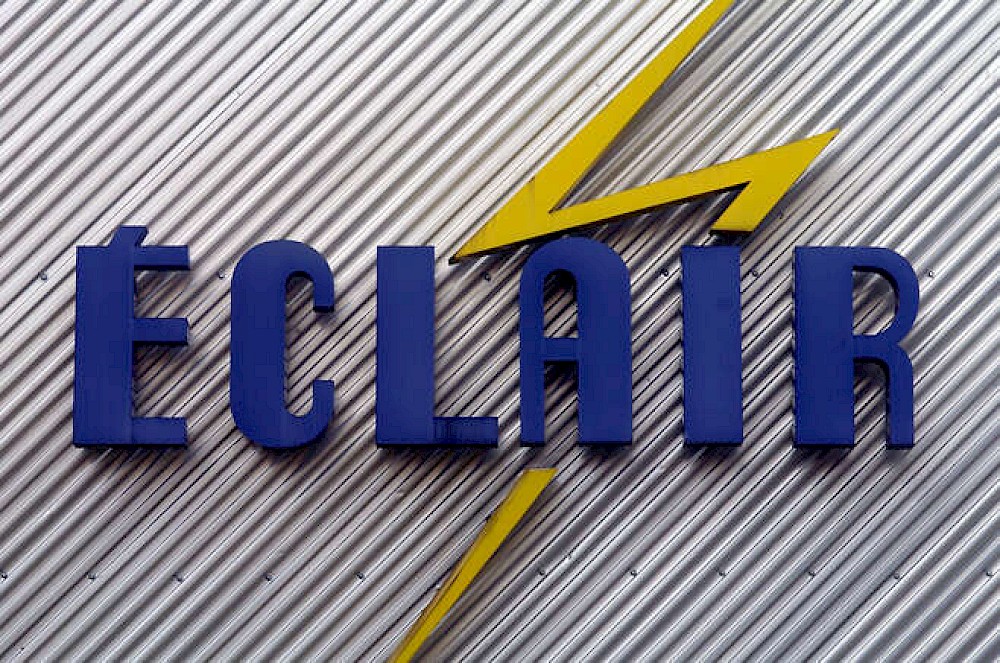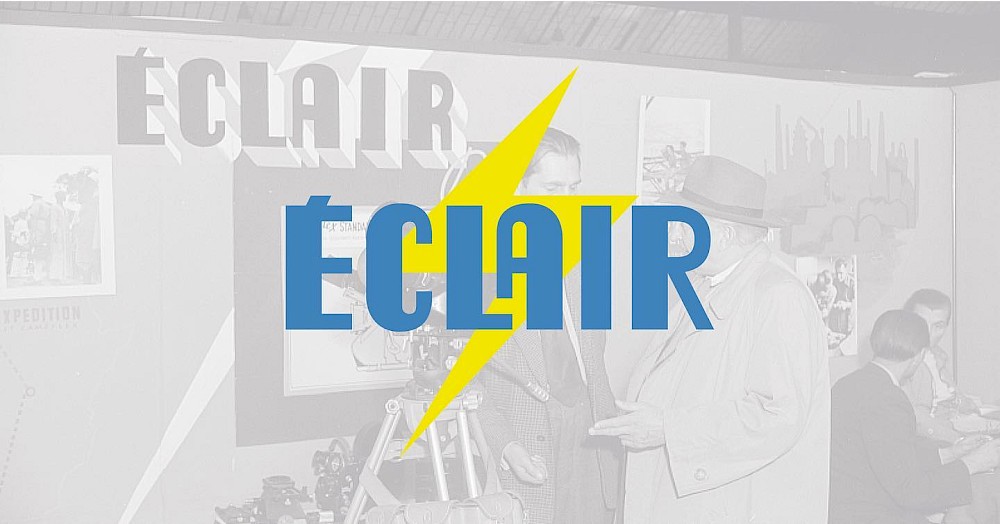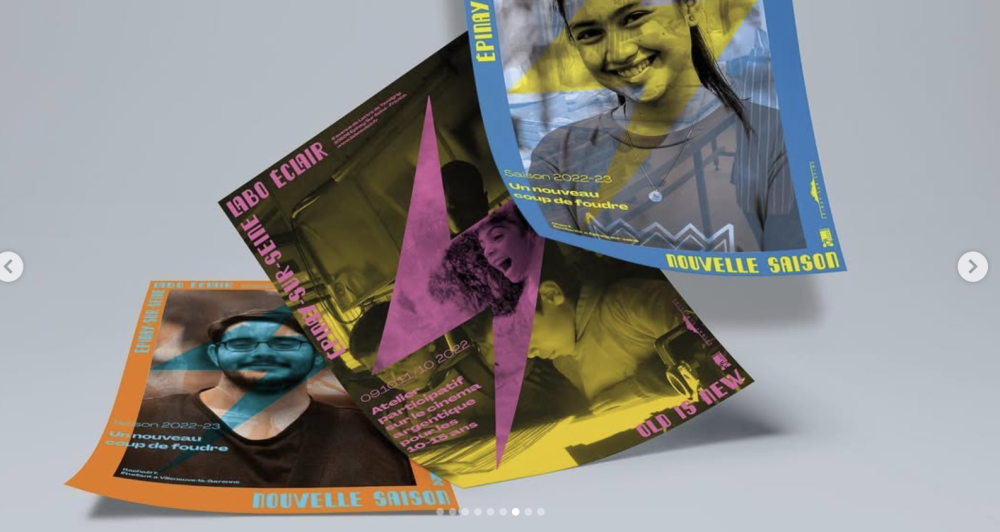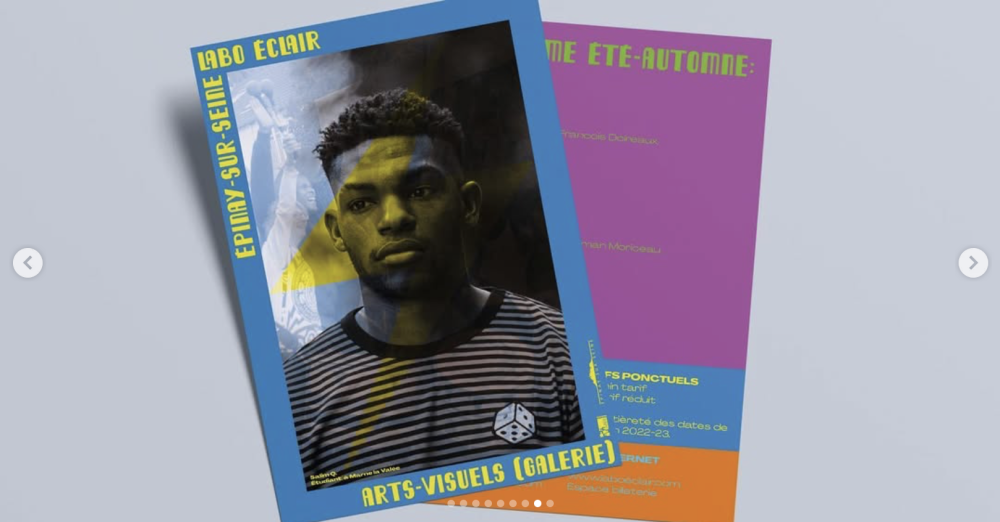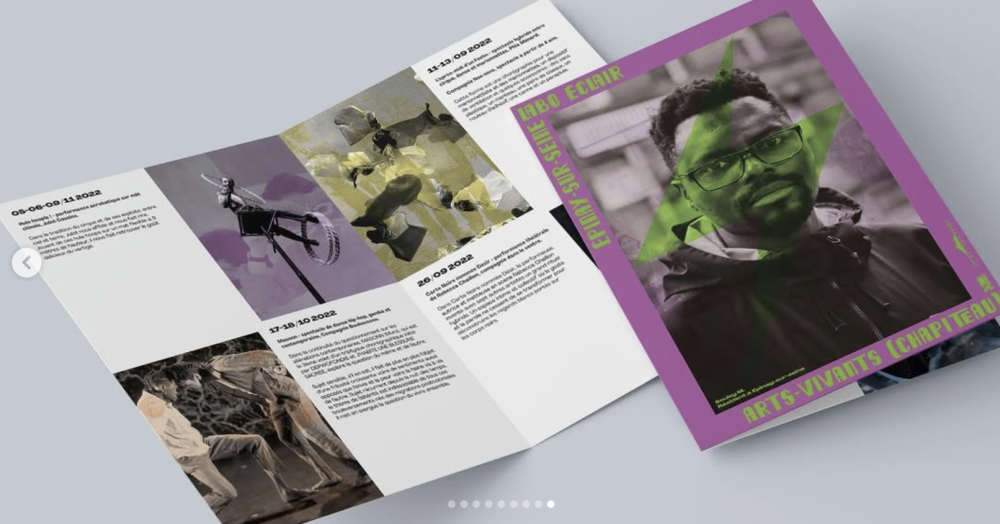
Labo Éclair — Issm_alien
Projet de diplôme DNMADE 2022. Création fictive de l’identité des « Laboratoires éclairs », à l’époque tiers-lieu culturel en devenir, basé sur l’ancien site portant le même nom. Créée en 1907 et fermée en 2013, la société Éclair fut un acteur majeur de l’industrie cinématographique, spécialisée dans les domaines de la production, puis du traitement photochimique, du coloriage, de la fabrication de caméras comme de la location de studios en France.
La création de l’identité a été basée sur la devanture du lieu, ornant le logo d’origine, ce qui a donné lieu à une refonte du logo et au dessin d’une typographie.
Labo Éclair